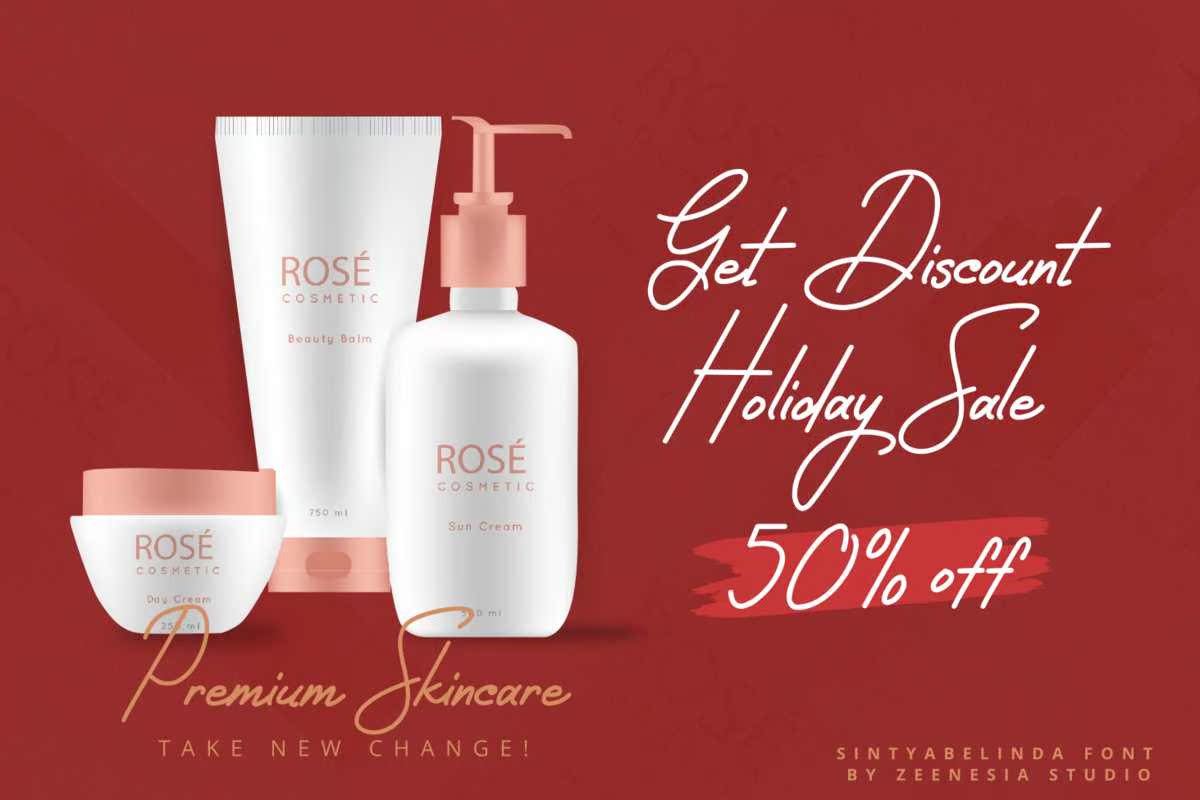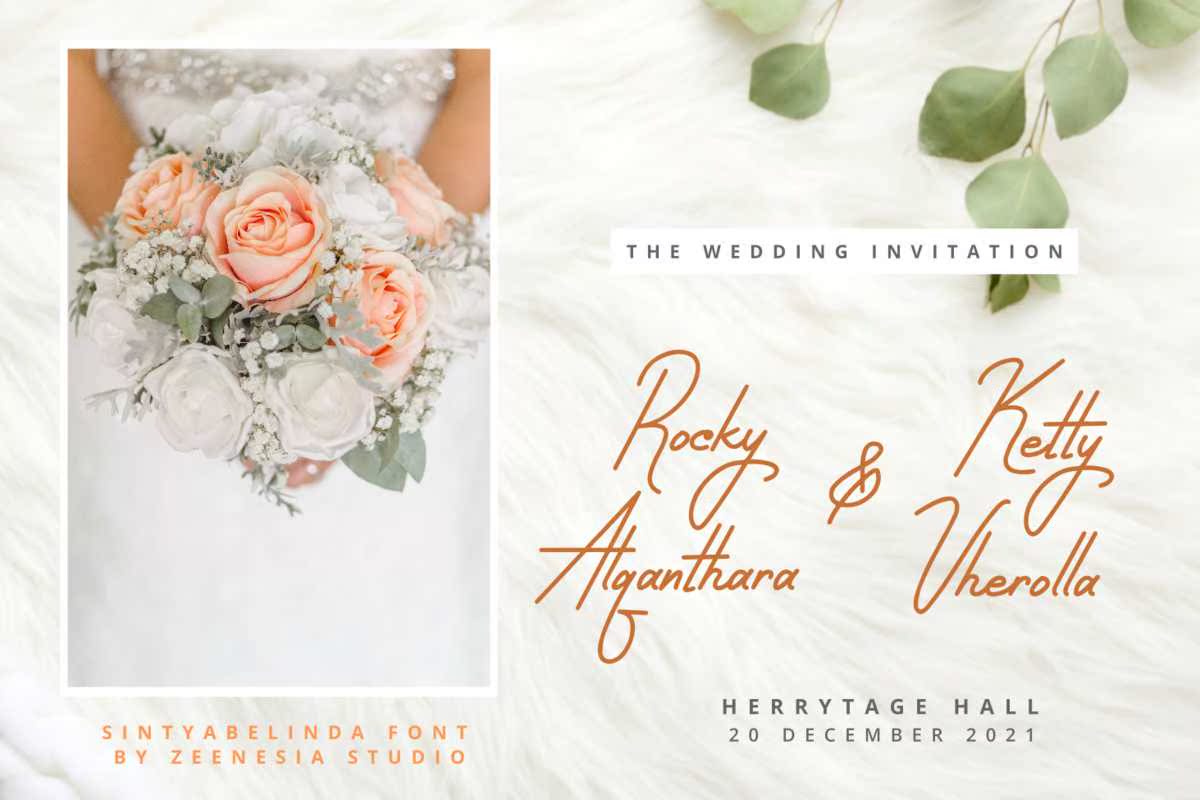
Sintysbelinda–Sintysbelinda是一种签名字体,适用于任何项目,包括徽标、品牌项目、家居设计、产品包装、杯子、报价、海报、购物袋、t恤、书皮、名片、邀请牌、欢迎卡、标签、照片、水印、特价品等。风格设置替代品和洗涤使该字体成为经典,这是您的收藏。谢谢。SintyBelinda–SintyBelinda是签名字体,适用于任何项目,包括徽标、品牌项目、家居设计、产品包装、杯子、报价、海报、购物袋、t恤、书皮、名片、邀请卡、欢迎卡、标签、照片、水印、特价、,还有更多。Stylegic SetAlternate and Wash使此Fonts经典,此FontWorthy成为您的收藏。谢谢。